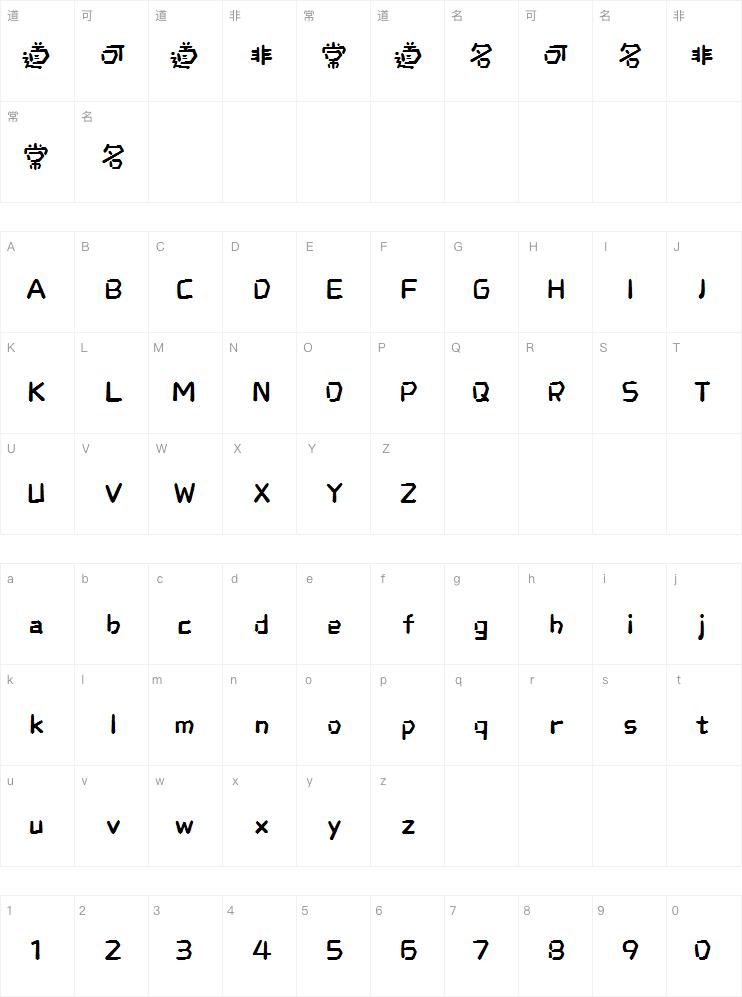
上首豆丁体
上首豆丁
上首豆丁体,简体中文约6763字。这套字体以 “稚拙灵动” 为核心气质,设计灵感源于手写草稿的随性笔触:笔画刻意做了轻微的 “歪扭感”,弱化印刷体的规整,保留手写的松弛感;结构上压缩字重、放大字符间的呼吸感,让字形像小方块一样紧凑又可爱,适配年轻化的排版场景(比如笔记、海报标题)。同时,字体在细节处做了 “童趣化处理”,偏旁部首的比例做了轻微夸张,强化 “豆丁” 般的小巧萌感,既能适配正文阅读(清晰度不打折扣),也能作为装饰字体突出活泼氛围。